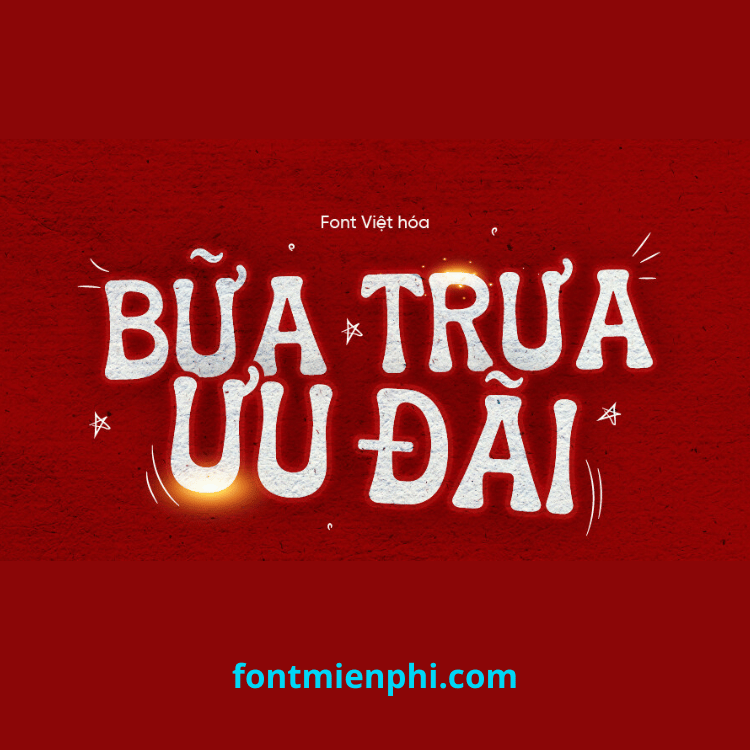
Font Việt Hóa 1FTV VIP Fruits Delight – Sắc Màu Tươi Mát Của Thiên Nhiên
1FTV VIP Fruits Delight là font chữ việt hóa độc đáo lấy cảm hứng từ thế giới trái cây tươi ngon. Với những nét vẽ sinh động kết hợp hình minh họa trái cây đáng yêu, font chữ này mang đến làn gió mới cho các thiết kế ẩm thực và mùa hè.
Ưu điểm vượt trội:
Bộ ký tự đặc biệt – tích hợp hình ảnh trái cây ngộ nghĩnh trong từng chữ cái
Màu sắc rực rỡ – phiên bản đa sắc và đơn sắc linh hoạt cho nhiều phong cách thiết kế
Hỗ trợ tiếng Việt đầy đủ – phù hợp với mọi nội dung quảng cáo ẩm thực
Ứng dụng sáng tạo:
- Thiết kế menu nhà hàng, quán trà sữa
- Poster quảng cáo thực phẩm, đồ uống
- Bao bì sản phẩm tươi sạch, organic
- Ấn phẩm truyền thông mùa hè
Khơi nguồn cảm hứng sáng tạo với 1FTV VIP Fruits Delight – nét chữ ngọt ngào như chính những trái cây mùa hè!